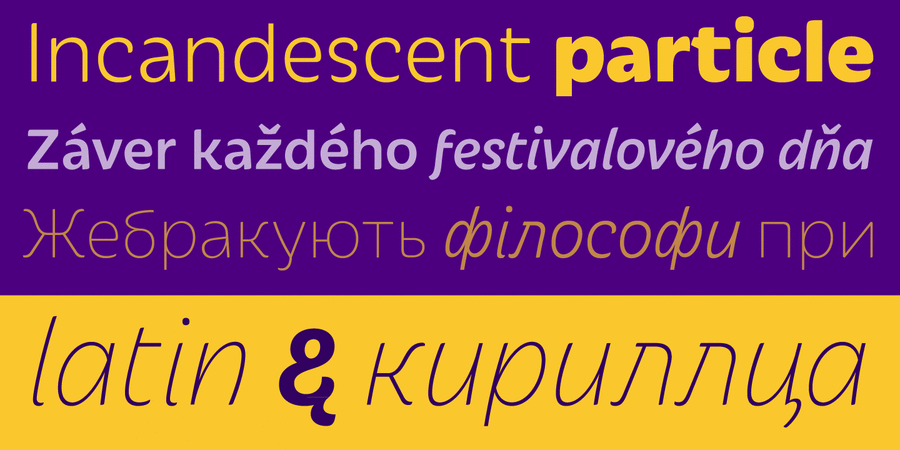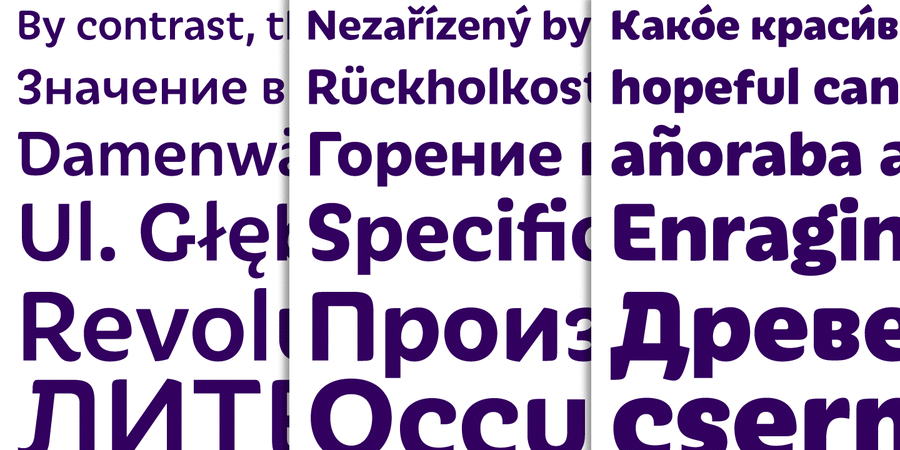
Iskra CYR (14 шрифтів)
Практичний гротеск не зобов'язаний бути сухим, точним та безхарактерним. Він може досягти успіху в своєї власної ролі та зберегти унікальний настрій. Iskra (Іскра або спалах) – новий шрифт без зарубок, розроблений Томом Грейсом. Він був задуманий як виклик поділу між утилітарними та декоративними шрифтами. Його привабливі форми відсилають до баскої пензлевої літерації та містять сміливі, елегантні вигини, економні пропорції та легку вертикальну асиметрії. Теплота цього шрифту виникає завдяки акценту на оригінальності конструкції та деталей окремих літер, тоді як його солідність проявляється у його збалансованому ритмі у великих обсягах тексту.
Кожне накреслення шрифту підтримує більше 60 мов і старанно адаптоване для використання як у друкарських виробах, так і на екрані. Iskra має 14 накреслень та чудово підходить для презентацій, журналів, брендингу та реклами.
Шрифт розроблено Томом Грейсом в 2011 році.
Асоціації з сімейством шрифтів Iskra CYRОсобистість і характер гарнітури:
делікатний, акуратний, лаконічний, якісний, холодний, худий, легкий, тонкий, чистий, невагомий, прозорий, повітряний, М'який, приємний, затишний, оригінальний, самобутній, цікавий, живий, динамічний, свіжий, весняний, ясний, природний, натуральний, елегантний, рухливий, красивий, комфортний, зрозумілий, доброзичливий, добрий, ввічливий, помірний, милий, органічний, зелений, довірчий, пластичний, гнучкий, гладенький, грайливий, симпатичний, зручний, ніжний, жіночний, привітний, позитивний, оптимістичний, неквапливий, літній, сімейний, домашній, смачний, няшний, радісний, чесний, здоровий, доступний, щасливий, теплий, соковитий, святковий, рукотворний, мультяшний, яскравий, виразний, помітний, мотивуючий, сильний, потішний, прикольний, ручний, важкий, товстий, дитячий, активний, щедрий